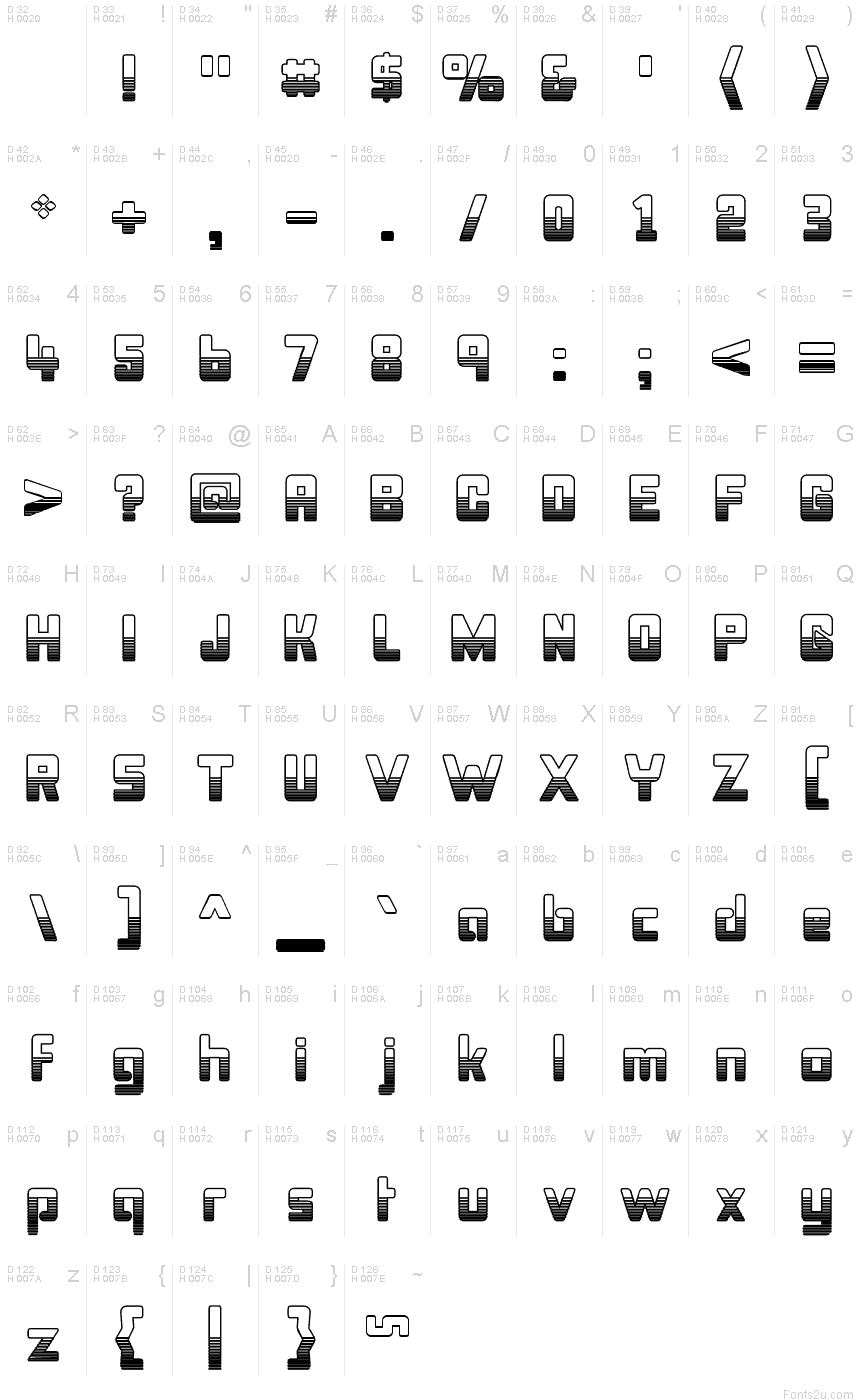
Krój pisma Bonk Outercut od Gemfonts to darmowy, groovowy font display z masywnymi, kwadratowymi kształtami, przeciętymi ciasnymi poziomymi paskami. Litery sprawiają wrażenie neonowych bloków, wydrążonych u góry i pasowanych u dołu, co nadaje każdemu słowu wyrazisty, mechaniczny rytm, który wciąż pozostaje zabawny. Te ostre warstwy linii natychmiast przyciągają wzrok, zamieniając nawet krótkie nagłówki w wyróżniające się grafiki.
Dzięki Bonk Outercut nagłówki nie tylko znajdują się na stronie – one pulsują jak szyldy automatów do gier. Ten darmowy font świetnie sprawdza się na plakatach imprezowych, ulotkach w stylu retro, okładkach albumów czy mixtape'ów, tytułach gier, miniaturach na YouTube i odważnych eksperymentach z logotypami. Warto łączyć go z czystym, lekkim fontem bezszeryfowym w tekście głównym, pamiętając o stosowaniu Bonk Outercut w dużym rozmiarze, aby prążkowane detale pozostały ostre i czytelne.